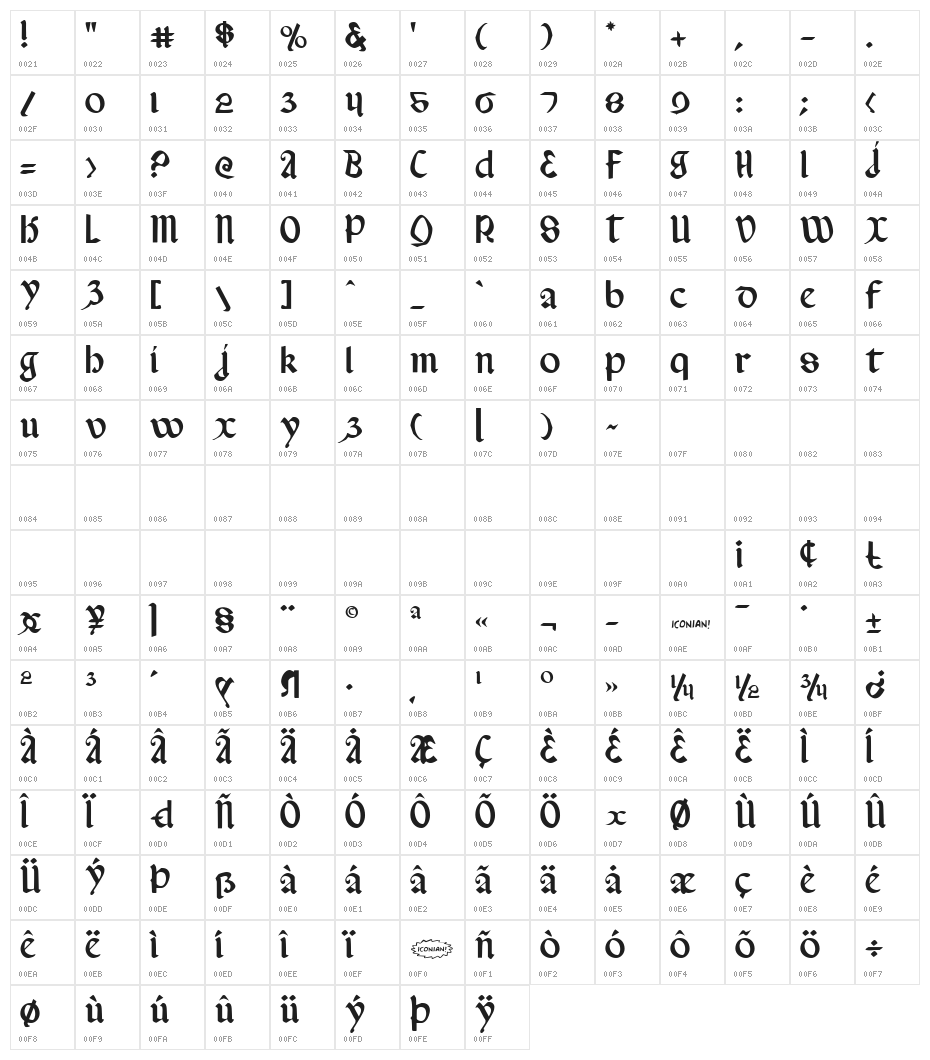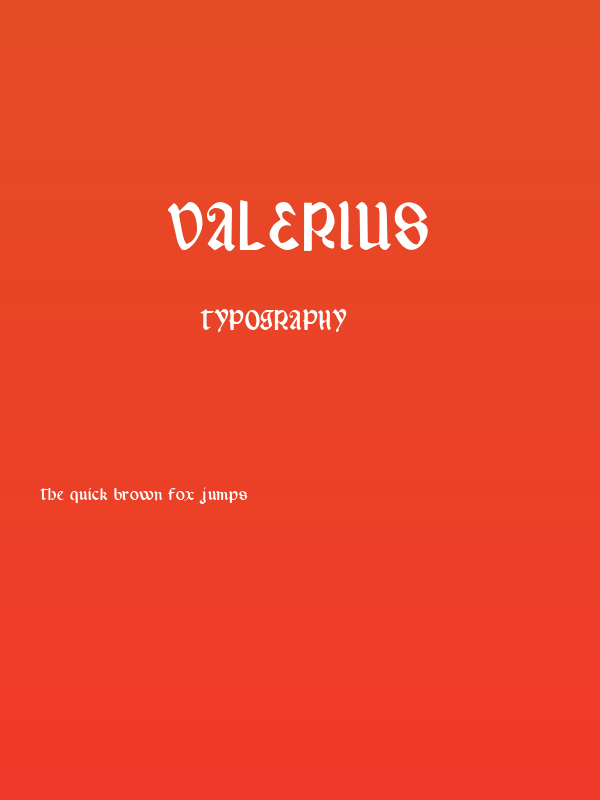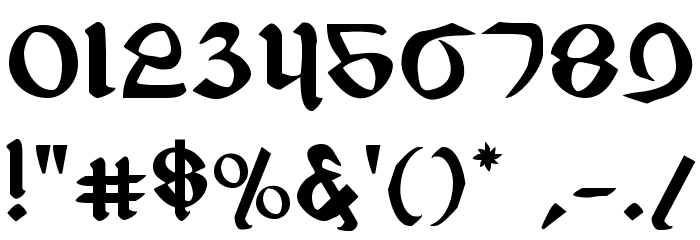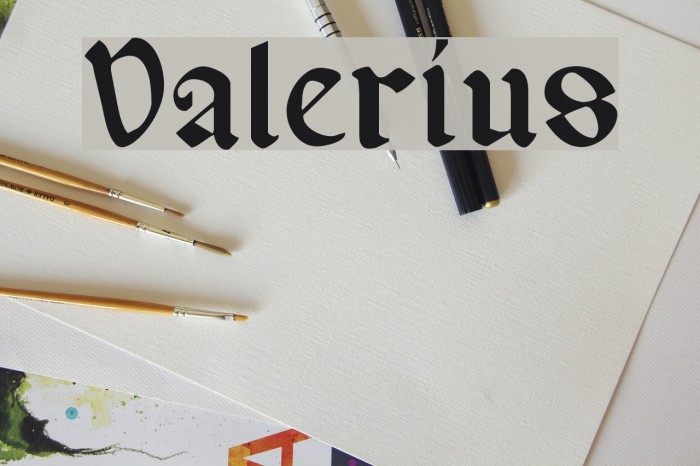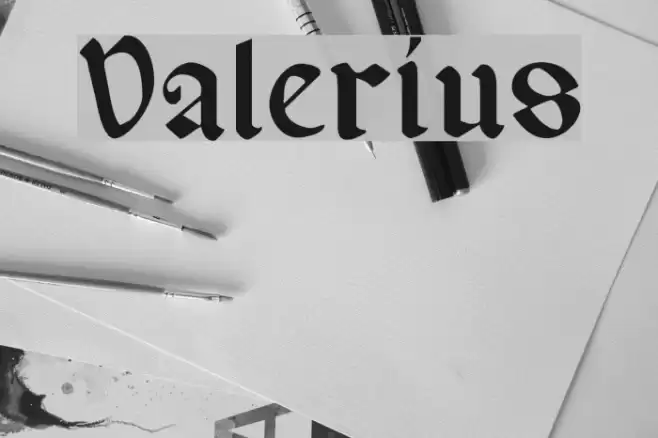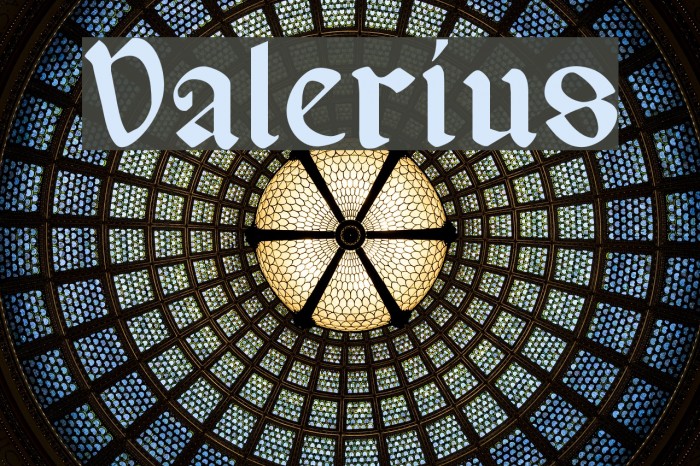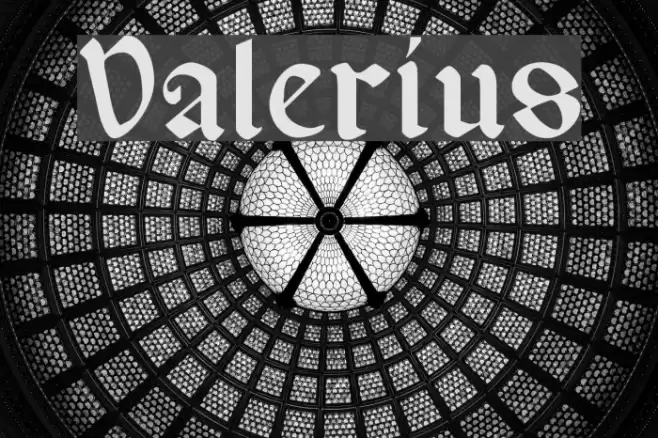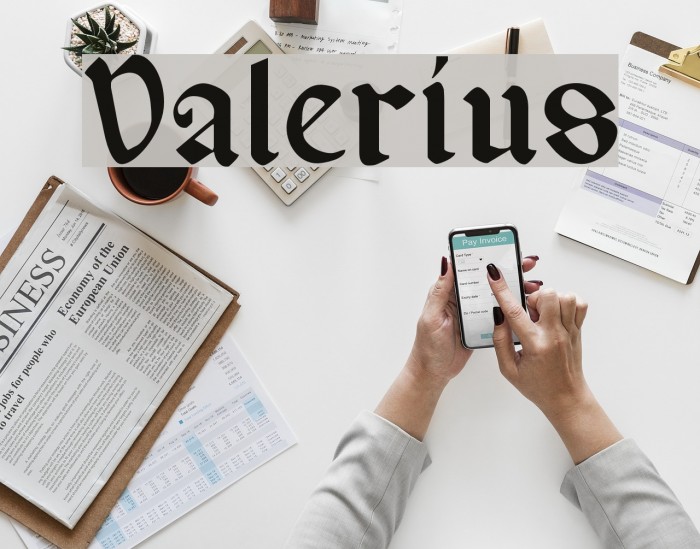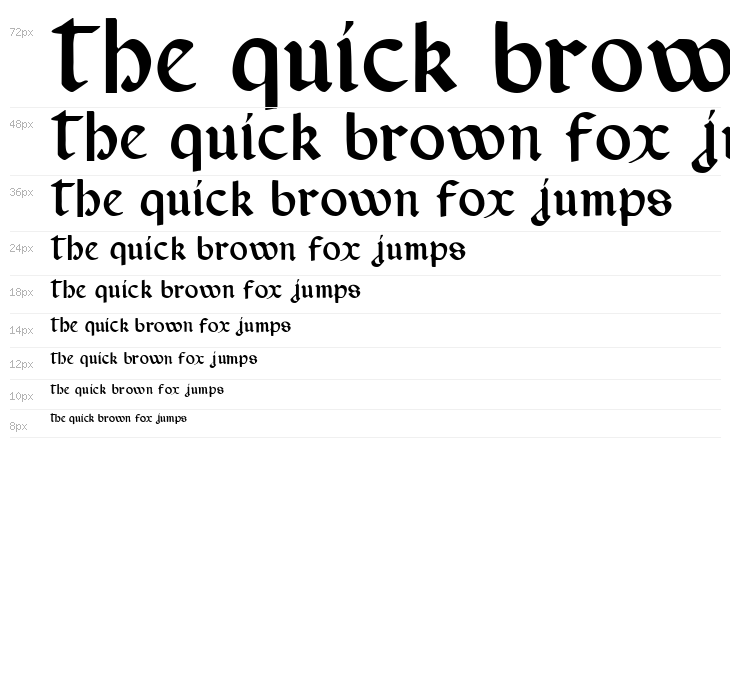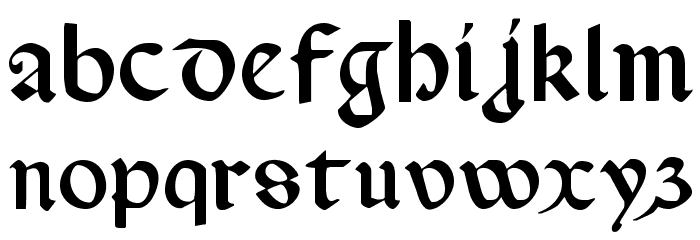
Valerius Font
✎ Gothic
| Categorias | Gothic |
| Caso de uso | Headlines, Logos, Decorative text |
| Projetos propostos | Ideal for certificates, invitations, book covers, and branding that requires a historical or formal touch. |